이웃나라 디자인 이야기.1_무사시노미술대학 활판인쇄 공방
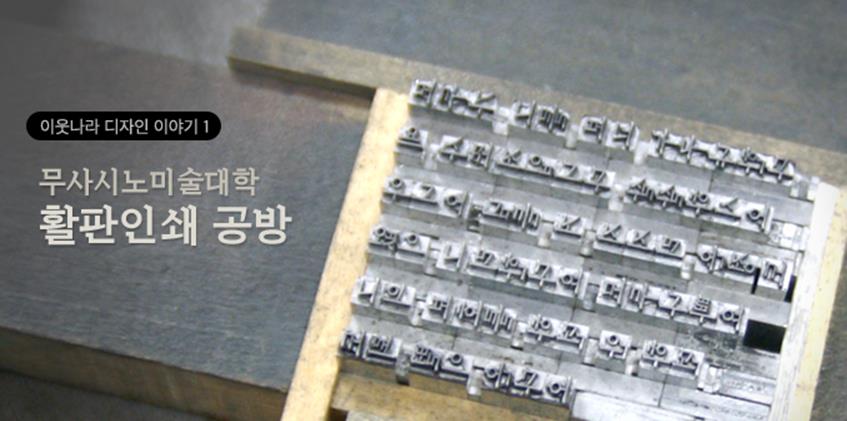
2012년 4월 무사시노 미술대학 시각전달디자인학과의 1학년 타이포그래피 수업에는 작업복 차림의 학생들이 활자 조판 테이블 앞에서 분주하다. 쾨쾨한 먼지냄새, 잉크냄새와 삐거덕거리는 기계 소리가 공방에 들어서는 순간 오랜 시간의 흔적을 느끼게 한다. 마치 타임머신을 타고 20세기 초, 중반으로 거슬러 올라간 듯한 광경이다. 학생들은 저마다 자신이 의도로하는 스케치를 들고는 활자와 스페이스의 납조각을 조판하느라 정신이 없다.
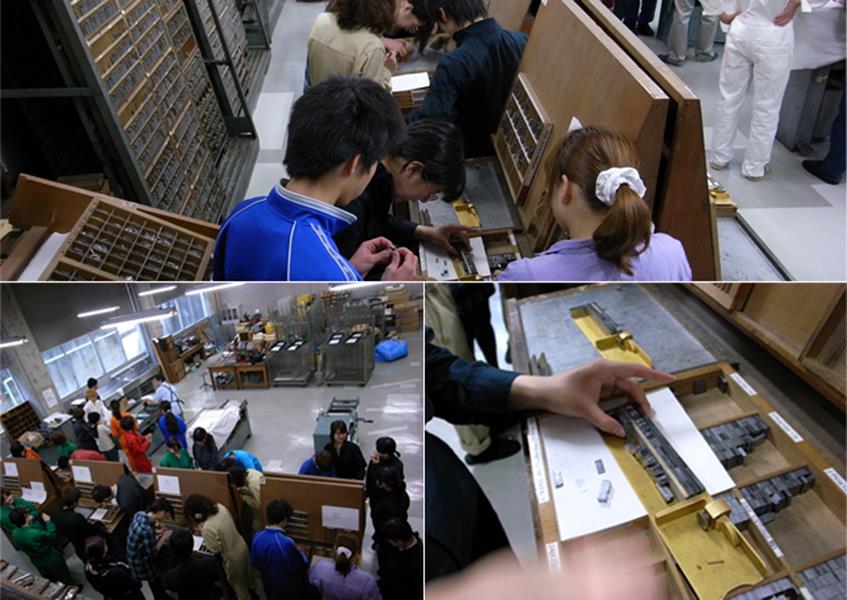
활판인쇄 실습 풍경
타이포그래피 수업의 기초과정으로 활판인쇄를 실습하는 내용은 매우 심플하다. 여러 패턴으로 자간을 설정해가며 자신의 이름을 조판 인쇄하는 것. 조판 후 인쇄기에 세팅하여 찍어내고 빨간 펜으로 자간을 체크하여 조판을 수정, 또다시 세팅, 인쇄, 수정하는 공정이 계속해서 반복된다. 컴퓨터를 사용하면 몇 분도 걸리지 않을 작업을 3주간에 걸쳐 활자와 씨름하는 과정으로 디자이너 지망생들의 문자 컨드롤이 시작된다. 컴퓨터 사용은 한참 이후의 작업이다.
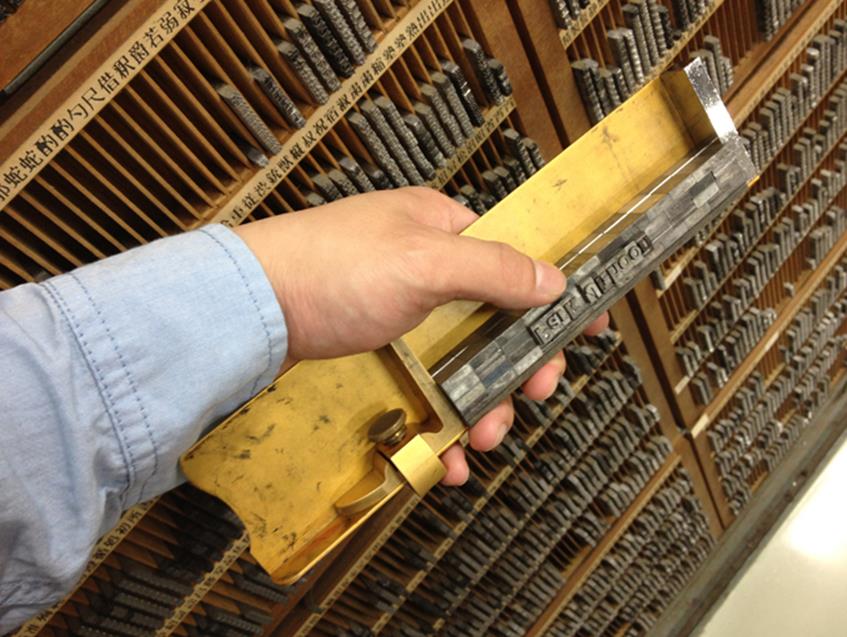
기초적인 활자 조판을 연습하고 있는 학생
종이 매체의 앞날을 걱정하고 있는 오늘날, 활판인쇄의 공정을 커리큘럼으로 채용하여 성적으로 반영하는 교육기관도 흔치 않은 것으로 알고 있다. 물론 여기에는 과거 문자 미디어의 체험이라는 단순한 명목 외에 또 다른 기대 목적이 있다. 과거 디자이너와 타이포그래퍼는 명확히 역할이 나뉘어있던 분야였으나, 컴퓨터 등 새로운 작업환경의 등장으로 그 구분이 점차 일치화 되어왔다. 이러한 환경에서 디자인을 공부하는 오늘날인 만큼 기초적인 활자 조판의 연습이 중요시된다는 것이 본 수업의 취지이다. 또한, 활자 사이에 스페이스 활자를 직접 끼워 넣으며 자간을 조절하는 과정에서, 문자 컨트롤과 가독성의 관계라는 기초감각을 손수 터득하게 한다. 아날로그 방식으로 공간의 컨트롤을 연습하는 과정에서는 문자사이즈의 배율관계 또한 직접 경험할 수 있다.
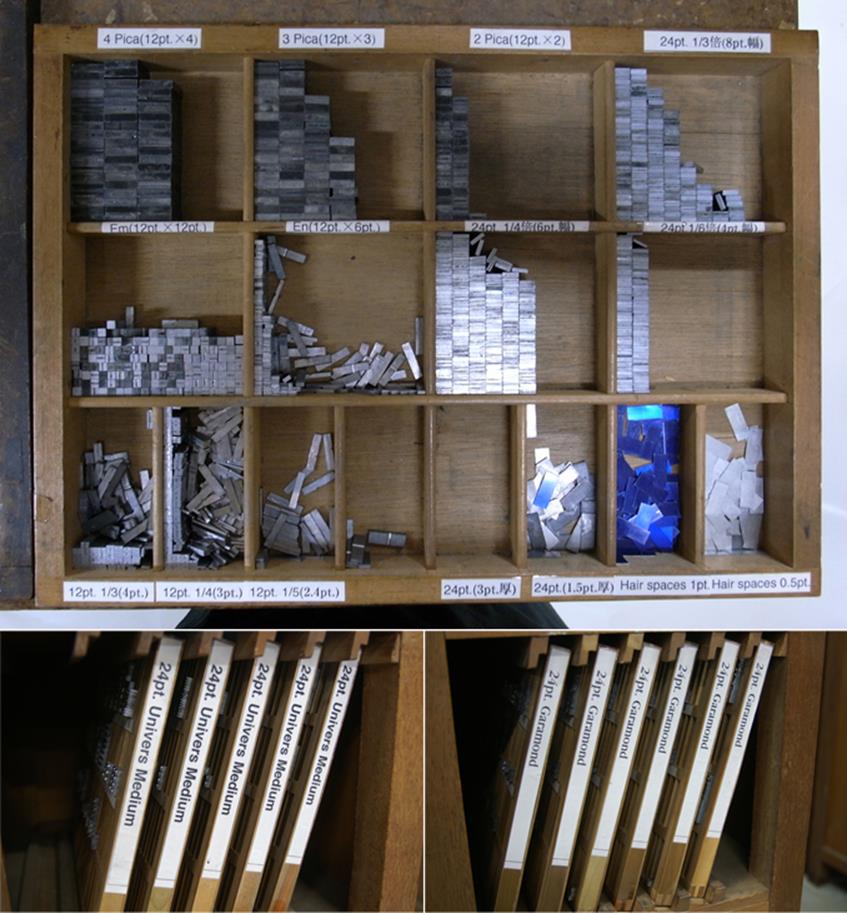
자간 조판시 사용되는 스페이스 칩, 유니버스 폰트, 가라몬드 폰트(아래)생
활판인쇄 실습은 로마 문자의 산세리프 활자로부터 시작된다. 문자를 컨트롤함에 있어 자간의 중요성을 인식시키려는 의도가 크다. 이후 수업은 시각적 요소가 많은 세리프체의 컨트롤 순으로 이루어진다. 활판인쇄 공방에는 한자와 가나 활자도 대량 구비되어 있으며 소량이긴 하지만 한글 명조체 활자도 찾아볼 수 있다.
1학년 타이포그래피 기초수업에서 활자 사용을 경험한 학생들은 2, 3학년 과정의 과제, 개인 작품 및 졸업작품 제작 등에도 활판인쇄를 활용하곤 한다. 최근에는 자신의 명함을 제작하거나 개인 전시의 안내장, 연말연시의 연하장 등을 제작하는 학생들도 자주 볼 수 있다. 인압을 가해서 눌러 찍어낸 명확한 검정이 일반 옵셋에서 느낄 수 없는 정보의 무게감, 진지함을 느끼게 한다는 것이 이곳 학생들의 의견이다.
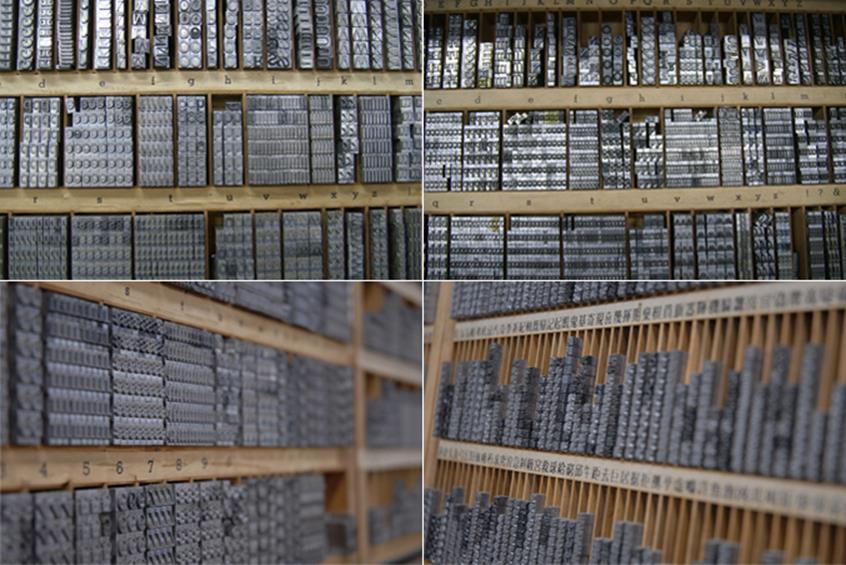
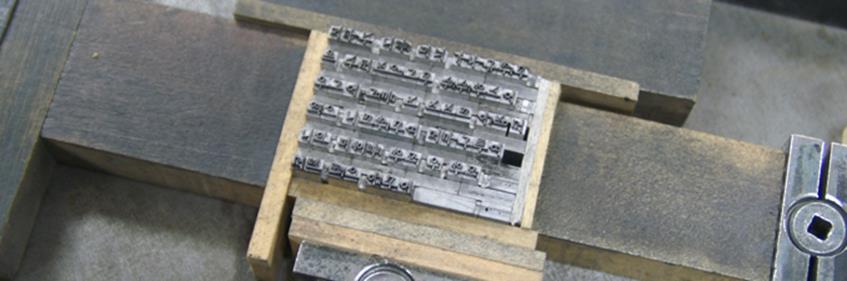
유니버스 폰트, 가라몬드 폰트, 영문 활자, 한자 활자, 한글 명조체 활자
수업에서 사용하는 인쇄기는 미국의 레터 프레스 프린터(Letterpress Printer)인 Vandercook이라는 기계를 사용하고 있는데, 학생들이 직접 조작하기에는 다소 조작법이 어려운 부분이 있어 주로 수업시간에 사용된다. 이미 부속품조차 찾기 어려운 골동품이지만 매년 수 차례에 걸친 점검과 정비 덕분에 아직도 두 대가 현역으로 문제 없이 움직인다.
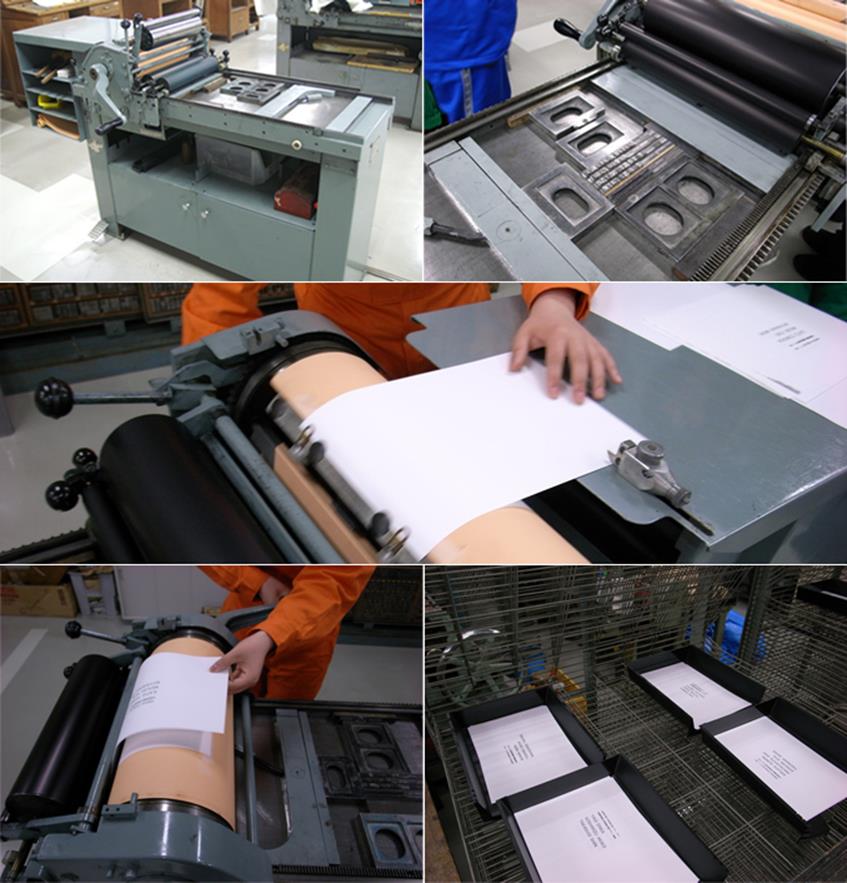
Vandercook Press
학생들이 개인적으로 사용하는 인쇄기는 Adana라 불리는 소형 수동인쇄기가 일반적으로 사용되고 있다. 엽서 사이즈의 소형 인쇄물에 주로 사용되지만 직접 롤러를 설치하고 잉크의 양, 인압 등을 손쉽게 조절할 수 있어 학생들도 쉽게 사용할 수 있으며, 활자 조판의 레이아웃에 따라서는 A4 사이즈까지도 인쇄할 수 있다는 점이 인기의 비결이다. 인쇄공방의 한 구석에는 옛 유럽의 삽화에서나 등장할 것 같은 프레스식 수동인쇄기가 한 대 녹슬어가고 있는데, 언젠가 학생들과 함께 이 기계를 되살려내려는 계획을 하고 있다. 활판인쇄 시스템의 기본적인 이해를 얻을 수 있는 좋은 공부모임이 될 것 같다.
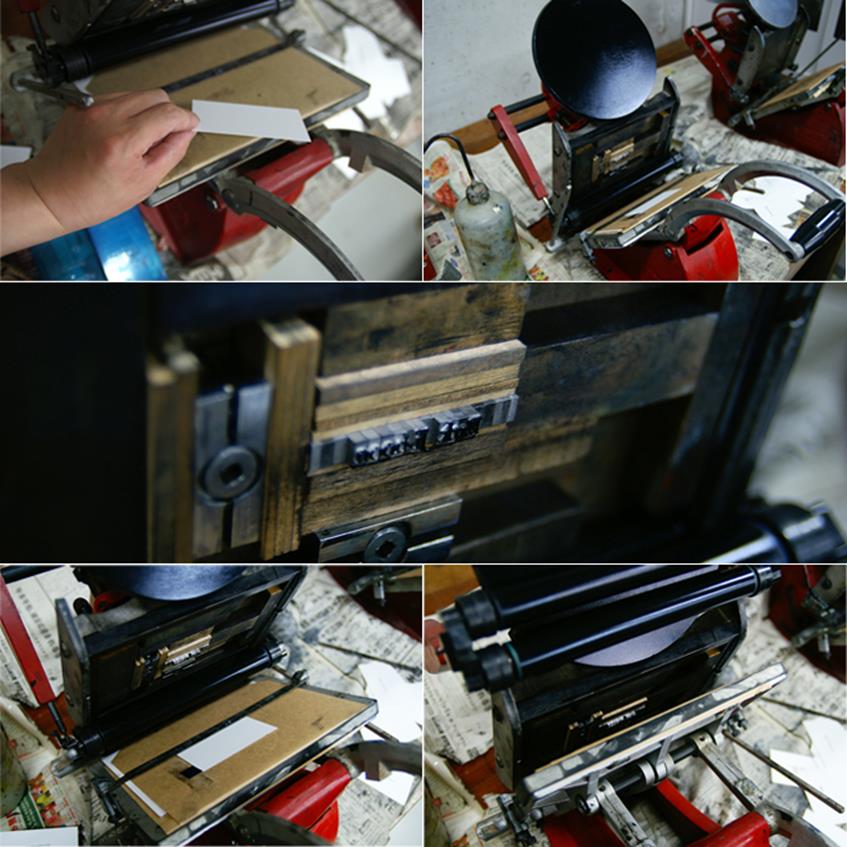
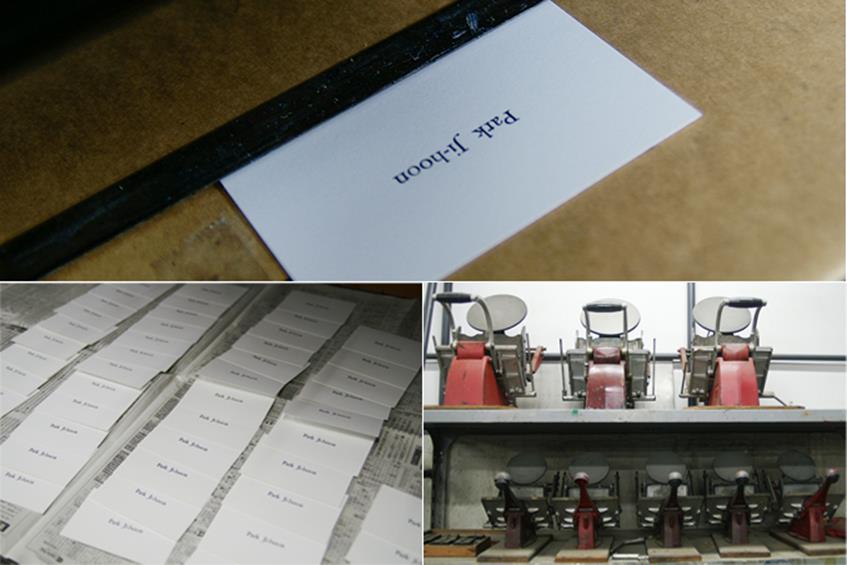
Adana Printing Press
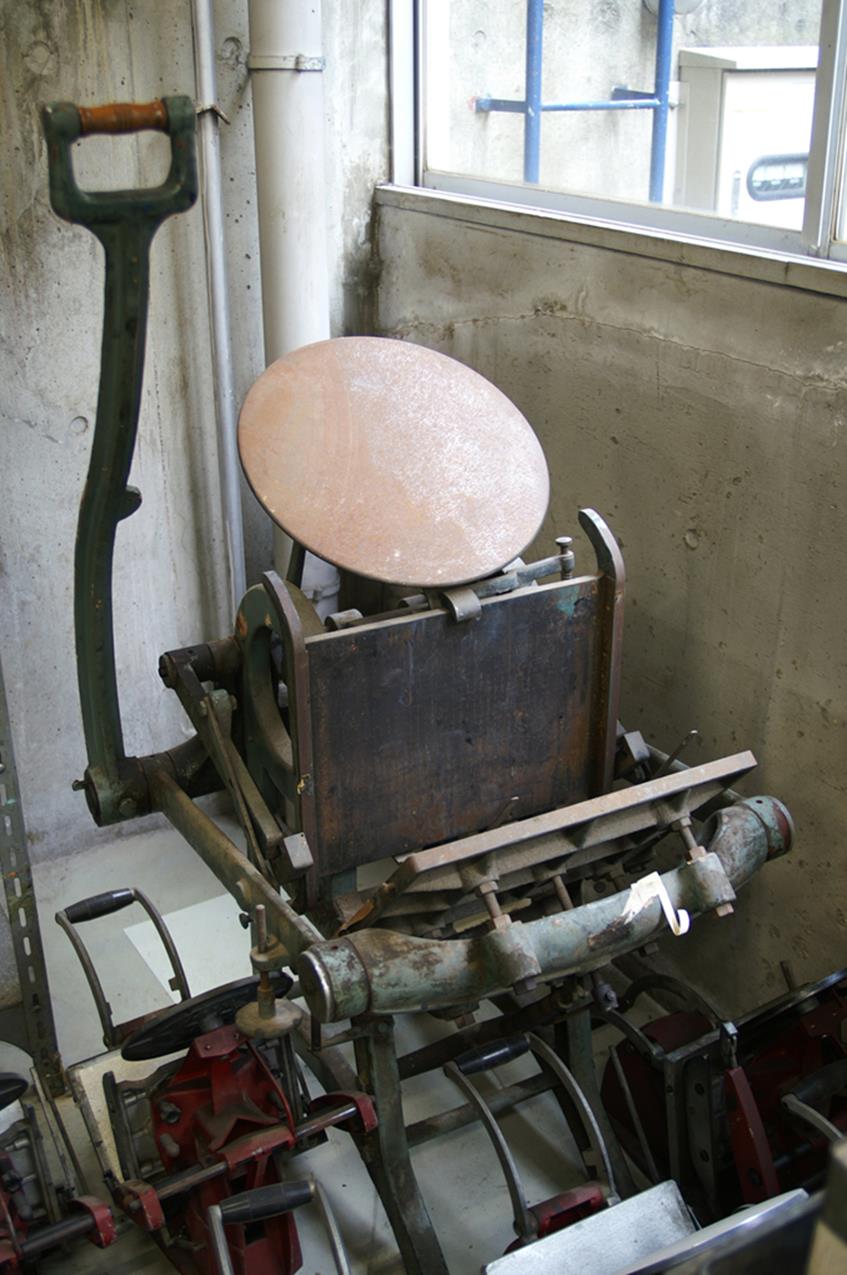
회생을 기다리고 있는 프레스식 수동인쇄기
이미 사라진 미디어로 인식되는 활판 인쇄가 아직 유지될 수 있었던 이유는 단지 보관, 관리의 문제를 넘어 일본 사회가 갖는 성격과도 관계한다고 본다. 실제로 활자를 제작 판매하고 있는 장인회사가 아직도 여러 곳에서 대를 잇고 있으며, 활판 기술을 이어받아 인쇄소를 운영하는 젊은 인쇄공들이 여전히 활판술의 맥을 잇고 있다. 물론 유지라고 해도 ‘매체’라는 수식어가 어색할 만큼 부분적으로 남아있는 상황이지만, 국내에서는 이조차도 찾기 어려운 실정이라, 한편으로는 약간 부러운 감정을 느끼고 만다.